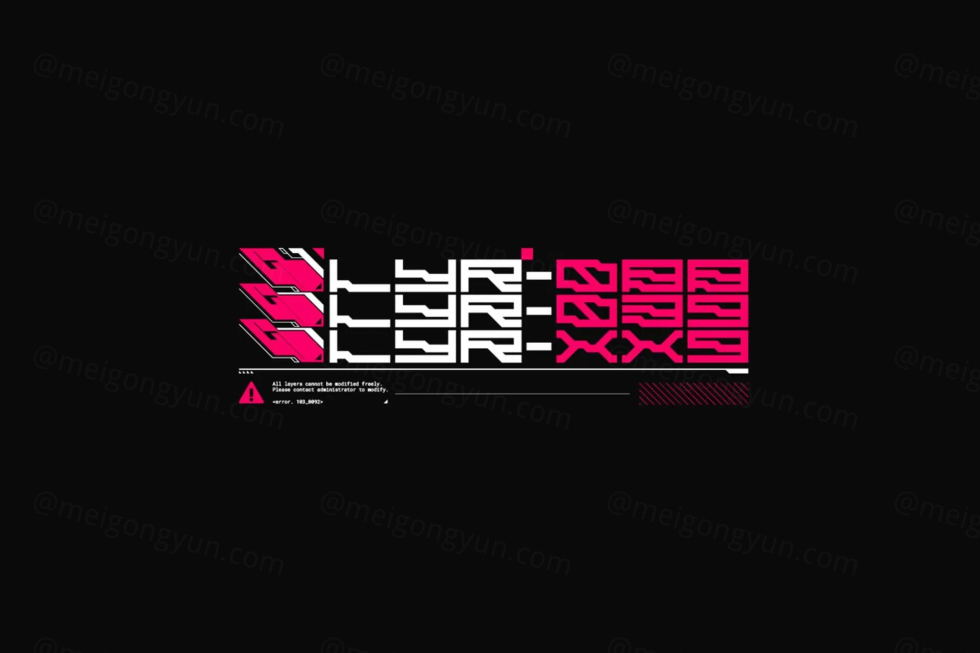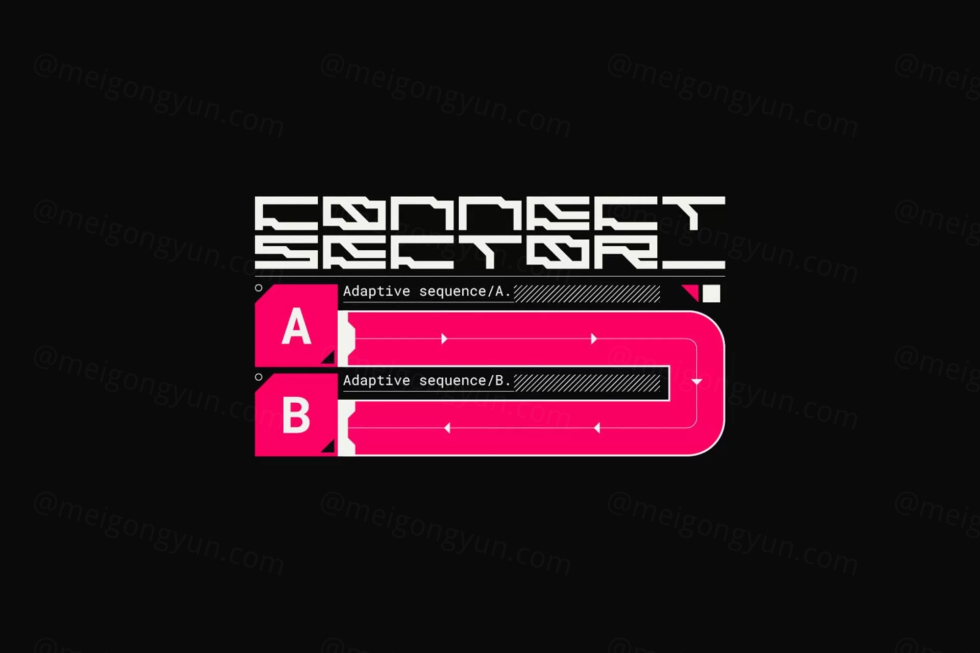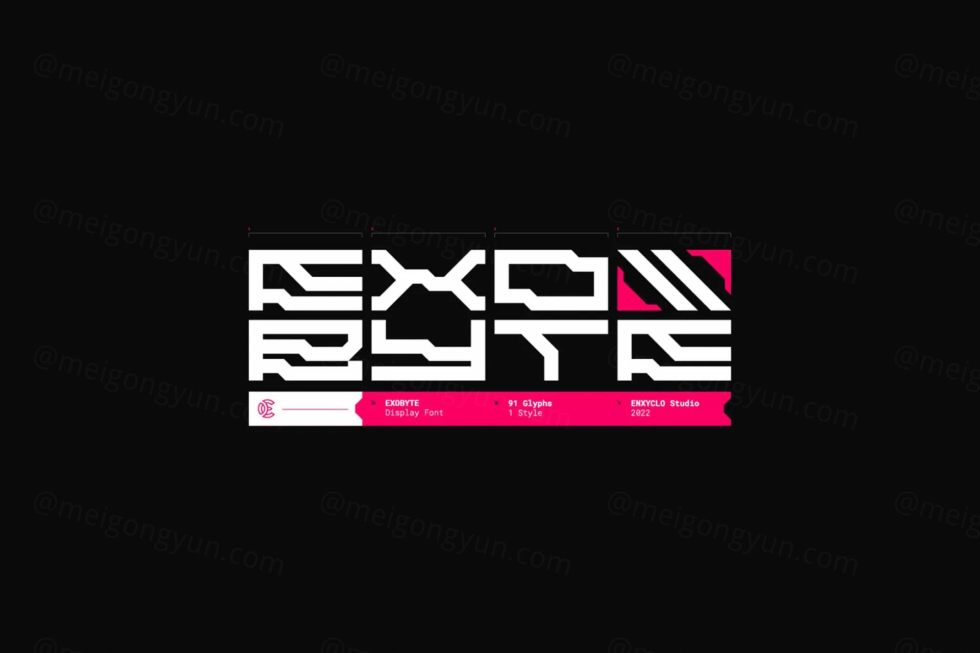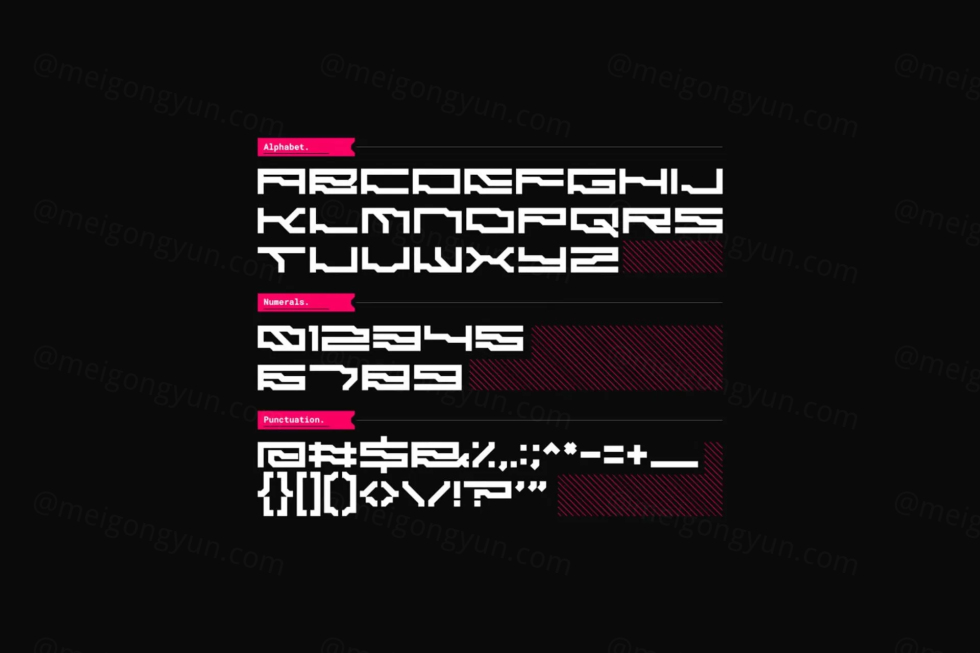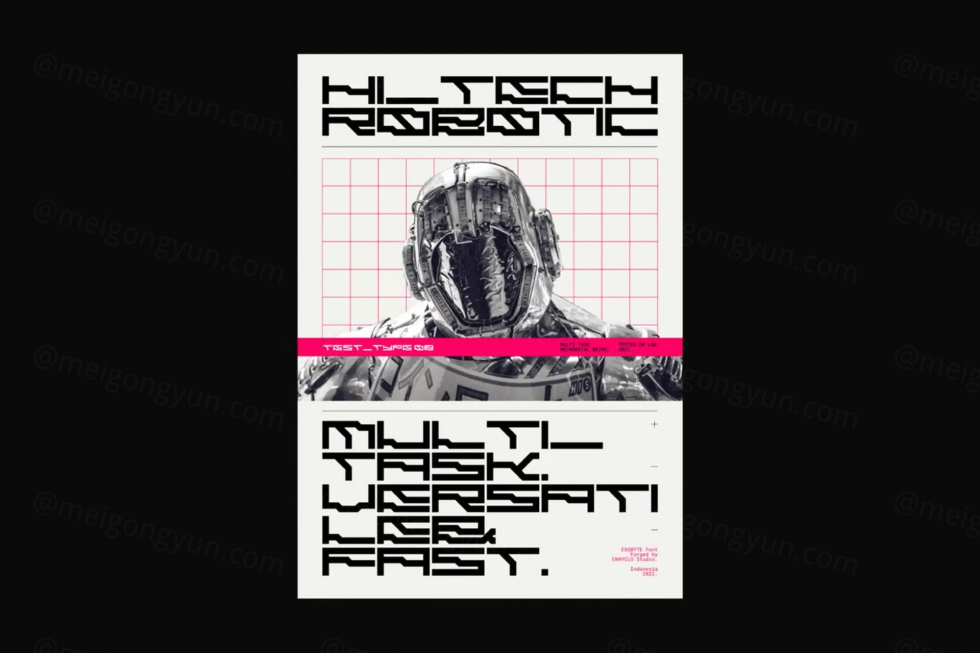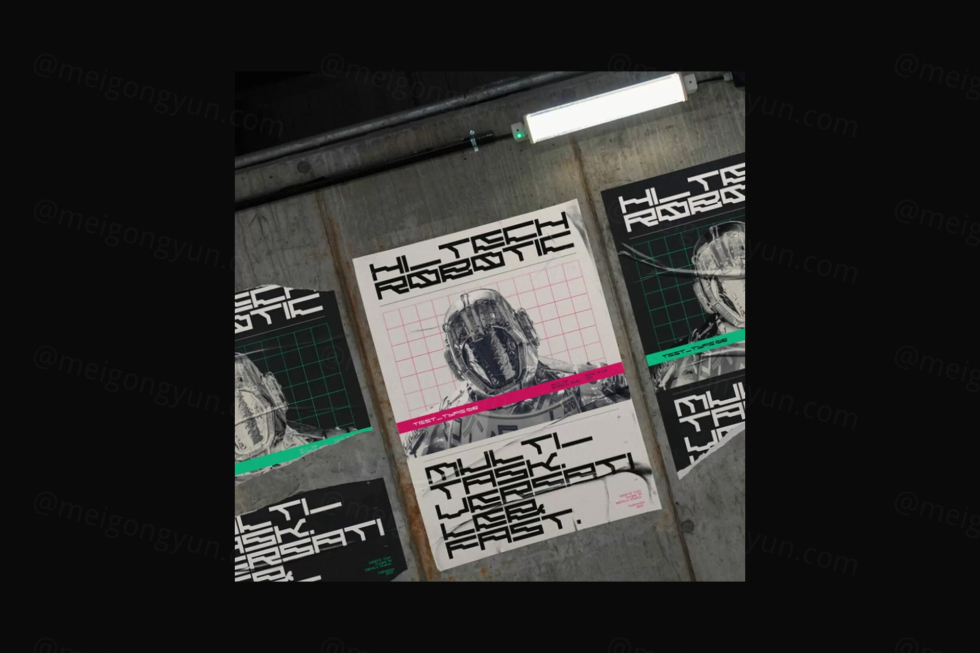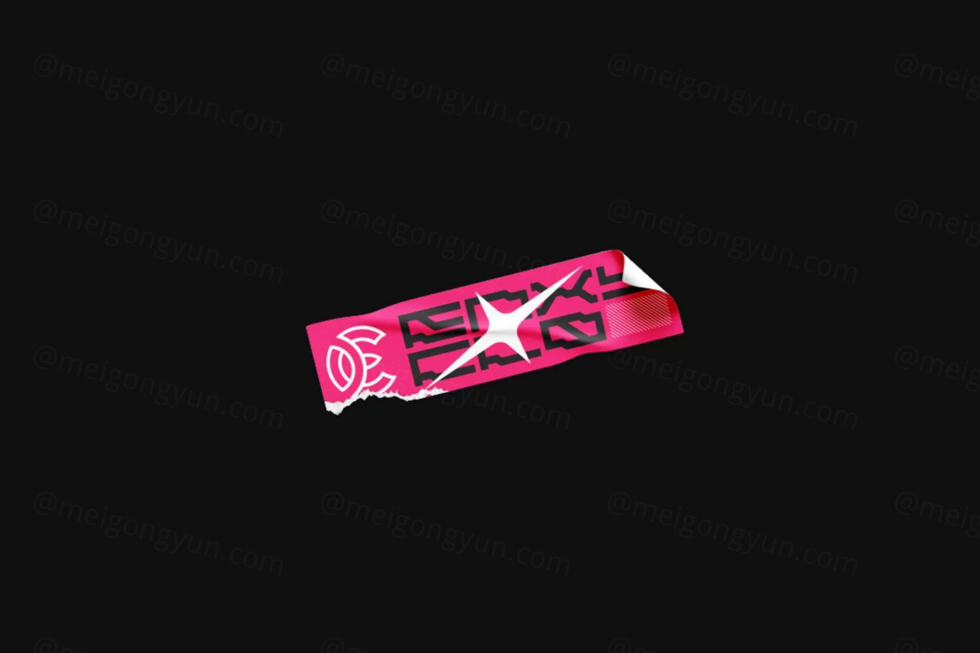
未来赛博朋克科技工业机能品牌潮牌设计几何抽象英文字体 Enxyclo Studio - EXOBYTE
EXOBYTE 是一种未来主义的显示字体。字体的设计增强了项目的力量和灵感,使其非常适合标题、广告牌、杂志、网站、标题、海报、品牌、缩略图、T 恤设计、街头服饰设计、创意徽标以及任何需要未来感的项目. 凭借其未来派的显示字体,您可以毫无疑问地将您的项目与其他项目区分开来。
– 包含 91 个字形
– 大写、数字、标点符号和符号